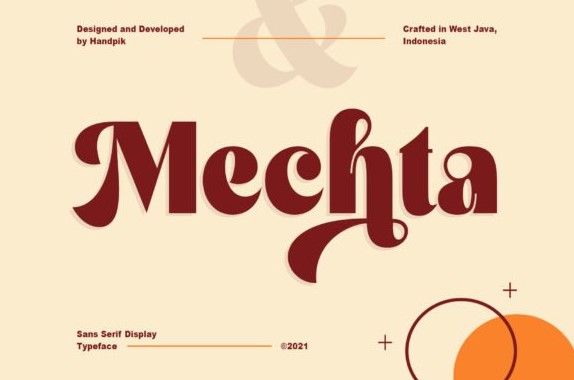
Creativefabrica Mechta Font 2021
[Creativefabrica] Mechta Font (2021)
Mechta - это модный и смелый шрифт, который отлично подходит для передачи любого сообщения с уверенностью, подлинностью и шармом.
Этот шрифт украсит широкий спектр идей, начиная от открыток и заканчивая брендингом, этикетками и многим другим.